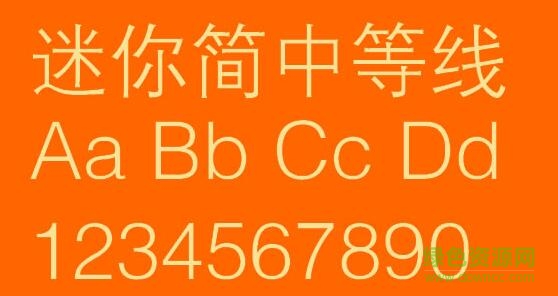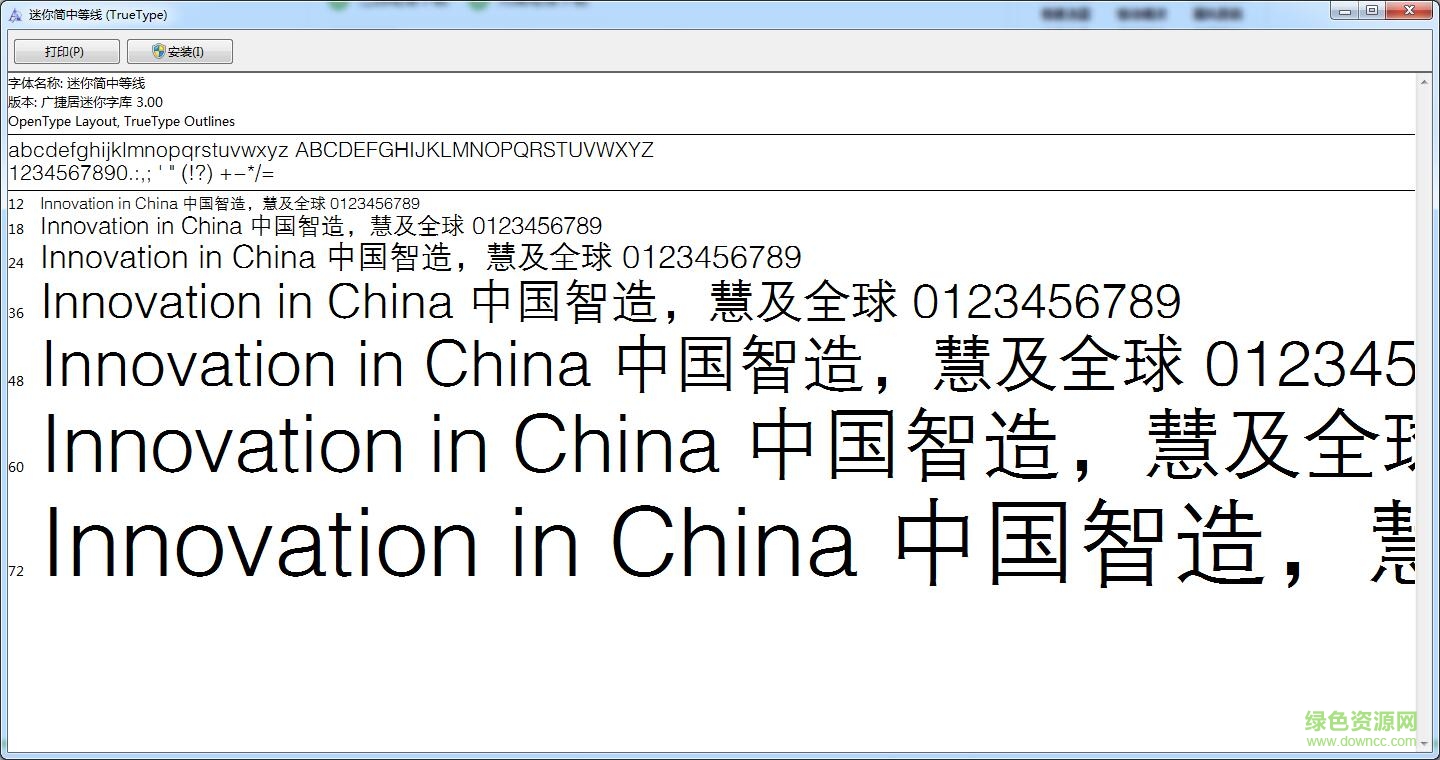
迷你簡中等線
迷你簡中等線字體是一套免費(fèi)的字體應(yīng)用。這款字體看起來比較大氣,常被用于設(shè)計、建筑行業(yè)使用。需要的用戶快來拿走吧!
字體介紹
迷你簡中等線是迷你字庫中的一種簡體中文字體,字體端正大方,粗細(xì)平均,可應(yīng)用于正文標(biāo)題、平面設(shè)計、廣告設(shè)計、雜志報刊等領(lǐng)域,歡迎用戶在綠色資源網(wǎng)下載使用!
迷你簡中等線字體